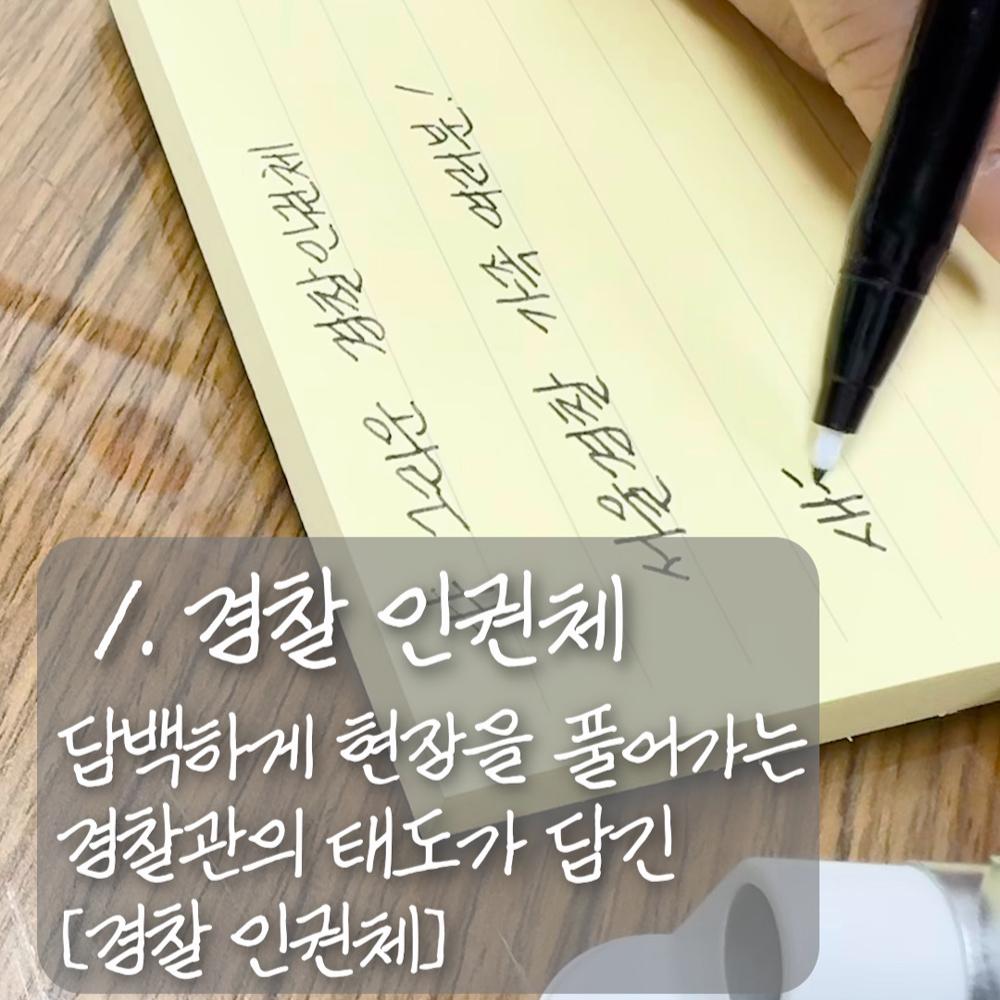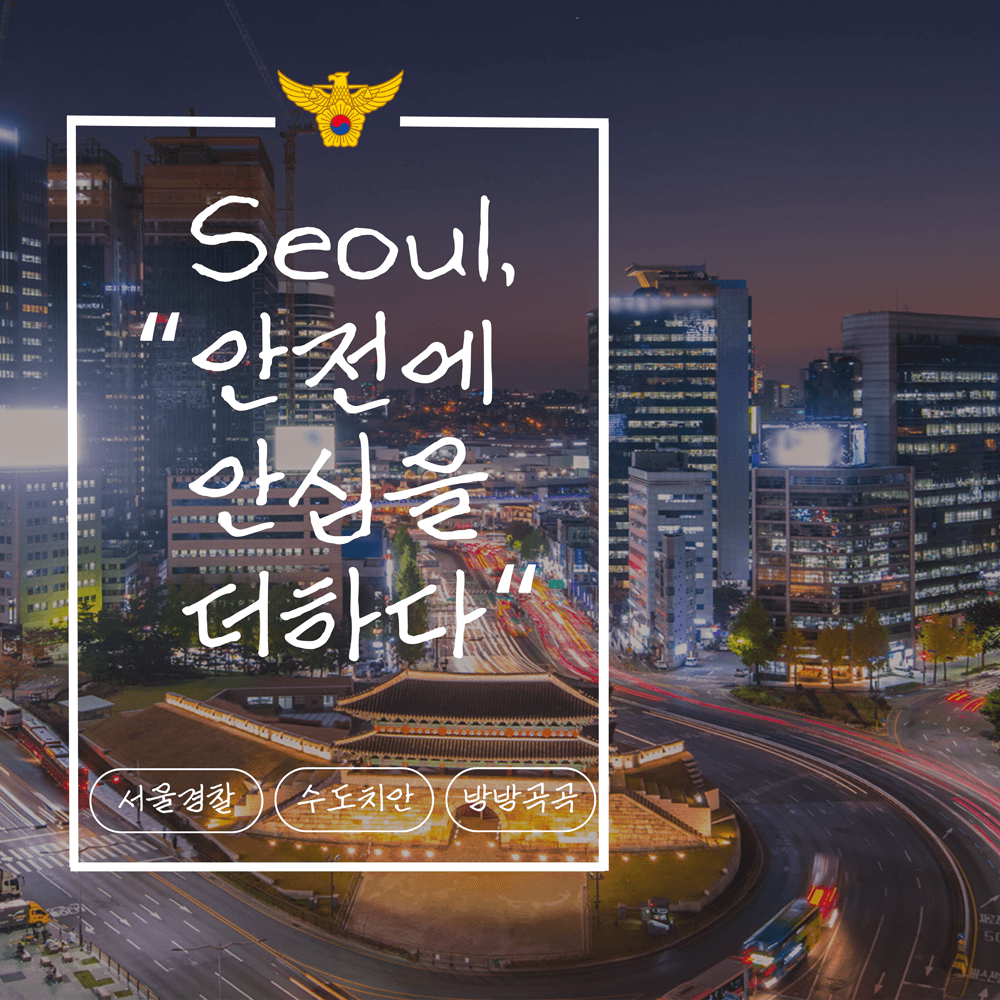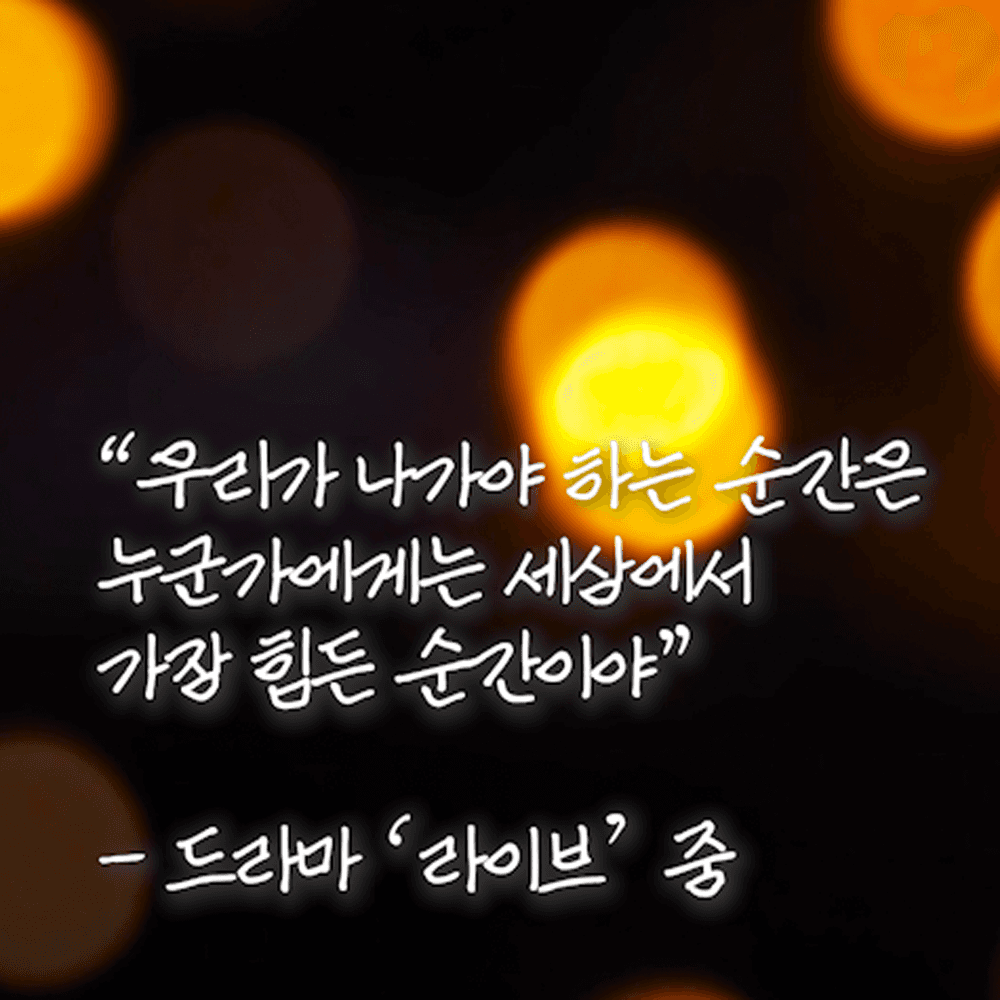
그리운 경찰인권체
Griun PolHumanrights
그리운 경찰인권체 소개
‘그리운 경찰인권체’는 서울경찰청(Seoul Metropolitan Police)과 그리운(Griun)이 공동 제작한 폰트입니다. 서울경찰 「인권손글씨 공모전」에 수상작으로 선정된 경찰인권체는 현장경찰관이 작성한 손글씨를 디지털 서체로 ‘최초’ 제작, 정갈하고 반듯한 느낌이 묻어나는 기본에 충실한 폰트입니다. 우리 모두의 안전과 인권을 수호하는 친근한 경찰 이미지를 표현하고자 인권체라는 폰트명으로 제작되었는데요, 우리의 다짐이 현실이 되어 여러분의 다양한 생활 속 이야기에 자연스레 포개어질 수 있도록 많이 이용해 주세요.